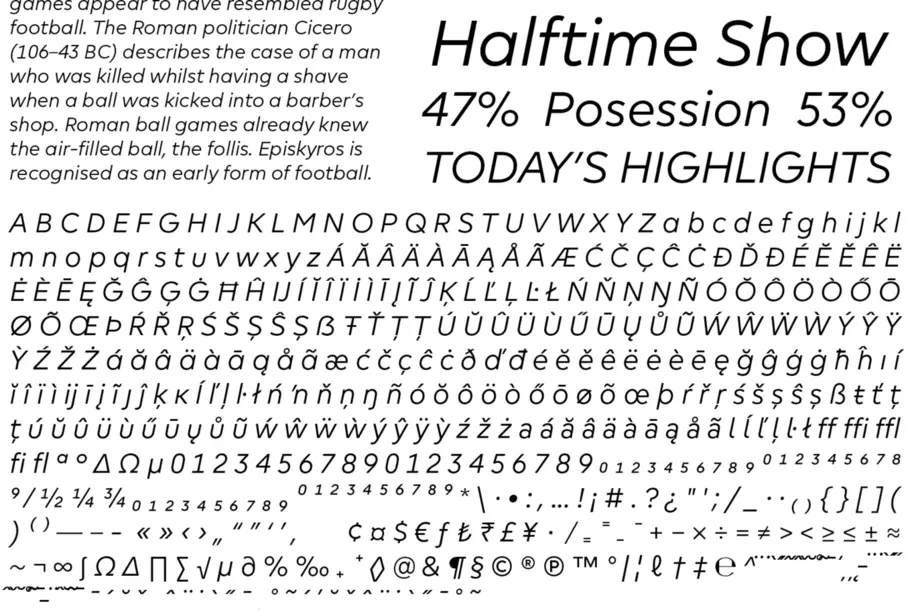
プレミアリーグ:最適化されたカスタム書体で、確かなブランドアイデンティティを発揮する
Monotypeの書体デザイナーである大曲都市は、DesignStudioと緊密に連携して、画面や背番号、テレビやリーグの成績表に至るまでの膨大な数のアイテムを通して、メディアが確実にユーザーへとそのブランドを認知できるような、確かなプレミアリーグ用のジオメトリックサンセリフを作成しました。
プレミアリーグでは、改定前はすべて大文字の書体を使用していましたが、今まで使用されていたフォントに真新しさと、親しみやすいイメージ、そして、さまざまなメディアで取り上げられても確実にブランドイメージをユーザーに届けることができるデザインを導入する必要がありました。ヨーロッパでのプロサッカーリーグとの激しい競争に常にさらされる中、プレミアリーグでは、視覚的な面だけでなく、商業レベルでも注目を集める必要があったのです。
フォント刷新前と刷新後のプレミアリーグのロゴ
「私たちは10年前にデザインされたフォントから、デジタル時代向けではないあらゆる要素を撤廃しようと考えました」と、DesignStudioチームは述べています。「ライオンとすべてのアイテムは、より美しくシンプルに感じられるよう描き直されました」DesignStudioは、大きなサイズでもインパクトがあり、デジタルアプリケーションで縮小された状態でもユーザーに正しく伝わるフォントを必要としていました。
書体は、大きなサイズで機能する必要があるだけでなく、成績表などを縮小版で使用する場合など、非常に小さなスケール(特に長い名前の選手を掲載できるようにするため)でも機能することが求められました。これには、イングランドのAlex Oxlade-Chamberlain選手の名前をテストケースとして使用しました。この実験は非常に珍しい印刷実験でした。
「このような取り組みを通じて、大文字と小文字が混在している場合には、線の太いフォントでは読みづらく、ユーザーに正しくブランドを伝えることはできないことがわかりました。この取り組みはとても興味深いものでした」
この書体の根底は、ブランド刷新の初期段階でDesignStudioが最初に描いた文字商標にありました。大曲はDesignStudioと密に連携し、たとえば、小文字のr、g、mのやや先が細くなったステムを挙げ、このようなディテールをファミリー全体のDNAとして反映させました。大曲は東ロンドンのDesignStudioのオフィスに常駐し、DesignStudioチームと協力して巨大なサイズで印刷される文字を作成し、DesignStudioの提案に沿って細かい調整を行っていきました。
「テレビやモバイルで背番号がよく使用されていることは分かっていましたので、背番号を他とは違う際立ったものにする必要がありました。」と、大曲は述べています。
Premier Sansは、テレビ、放送、印刷物、ウェブサイト、アプリ、そして地上のあらゆる接触点(タッチポイント)に対応できるフォントである必要がありました。それだけではなく、ブランドの新しい印象を伝え、そのブランドの持つ特徴を正しく示すことができるということも必要不可欠な要素でした。
「Premier Sansは、基本的には機能的な書体ですが、さりげなくフレアで装飾することもできます」と、DesignStudioは付け加えています。
「 今、人々がサッカー観戦を楽しんでいる時、その気をそらすのはモバイルやコンピュータです。これは他のスポーツブランドと同じくらい手強い競争相手です。 」
「DesignStudioでは大曲氏と協力し、より印象に残る文字の研究に取り組んでから、数字と句読点に移りました。この取り組みでは、ひとまとまりの文字として読まれることはないものの、拡大され見出しで使用されてもブランドの特徴を伝えることができるものを追求しました」
モバイルやコンピューター上で多用されているジオメトリックサンセリフとの違いは、縦線の上部に加えられているわずかな角度です。特に数字には最も注意を払いました。時計、成績表などを画面上で使用する際には容易に区別できる必要があるためです。
「テレビやモバイルで数字がよく使用されていることはわかっていましたので、背番号を他とは違う際立ったものにする必要がありました」と、大曲は述べています。
また、この書体は視覚的に新しいプレミアリーグを印象付ける一助となり、同業のスポーツ団体だけでなく、世の中に新しいものを発信し先導し続けているGoogleやAppleなどの先駆的企業とも同様の世界観をプレミアリーグでも持たせることに成功しました。
「私たちは、よりパーソナルでオープンなイメージをもつ書体を追求しました」と、DesignStudioは付け加えます。「このようなブランドフォントの世界観は現代的(コンテンポラリー)であると言えるでしょう」